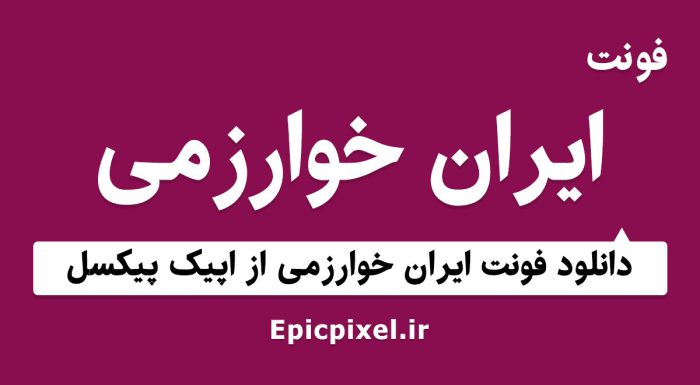
فونت ایران خوارزمی فارسی
فونت ایران خوارزمی یک فونت فارسی جدید و مدرن
اگر به دنبال یک فونت فارسی جدید و مدرن هستید که برای طراحی گرافیک، نشر محتوا و رسانههای اجتماعی مناسب باشد، ما به شما فونت ایران خوارزمی را پیشنهاد میکنیم. فونت ایران خوارزمی یک فونت بسیار زیبا و حرفهای است که با تلفظ و قلم فارسی همخوان است و به شکل و شخصیت زبان فارسی توجه دارد. در این مقاله، ما قصد داریم به شما معرفی کنیم که فونت ایران خوارزمی چیست، چگونه میتوانید آن را دانلود و نصب کنید و چه کاربردهایی برای آن وجود دارد. همچنین، نظرات کاربران درباره این فونت را با شما به اشتراک میگذاریم و به سؤالات متداول شما پاسخ میدهیم.
معرفی فونت ایران خوارزمی
فونت ایران خوارزمی یک فونت فارسی است که توسط شرکت ایران خوارزمی طراحی و تولید شده است. این شرکت یکی از پیشروان در زمینه تولید نرمافزارهای زبانشناسی، هوش مصنوعی و طراحی گرافیک است و با هدف ارتقای کیفیت و استاندارد زبان فارسی در فضای مجازی فعالیت میکند. فونت ایران خوارزمی یکی از جدیدترین و محبوبترین محصولات این شرکت است که در سال ۱۴۰۲ روانه بازار شده است.
تاریخچه و منشأ فونت ایران خوارزمی
فونت ایران خوارزمی بر اساس الگوریتمهای پیشرفته هوش مصنوعی و زبانشناسی طراحی شده است. این فونت با تحلیل دادههای بزرگ متنی فارسی، الگوهای زبانی، ساختار صوتی و نگارشی، تلفظ و قلم فارسی را شناسایی و بهینهسازی کرده است. هدف از طراحی این فونت، ارائه یک فونت فارسی با کدگذاری استاندارد، قابل خواندن، مناسب برای صفحات وب و رسانههای دیجیتال، هماهنگ با زبانهای دیگر و دارای زیبایی بصری است.
فونت ایران خوارزمی دارای ويژگيها و مزاياي بسياري است كه برخي از آنها عبارتند از:
قابليت پشتيباني از زبانهاي ديگر با الفباي لاتين (انگليسي، فرانسوي، آلماني، اسپانيولي و …)
قابليت نمايش در سطح بالا در صفحات وب با رزولوشنهاي مختلف
قابليت حفظ كيفيت در چاپ با رزولوشنهاي بالا
قابليت تغيير اندازه، رنگ، ضخامت و فرم بدون از دست دادن زيبايي و خوانايي
داراي حروف و اعراب منحصر به فرد و متناسب با شكل و شخصيت زبان فارسي
داراي انواع حروف ساده، پررنگ، كج، ضخيم و نازك
داراي انواع علائم نگارشي، رياضي، علمي و فني
داراي انواع ارقام فارسي، عربي، انگليسي و رومي
داراي انواع سمبلها و آيكونهاي گرافيكي
کاربردهای فونت ایران خوارزمی
فونت ایران خوارزمی یک فونت چند منظوره است که برای کاربردهای مختلف مناسب است. در این بخش، ما به برخی از کاربردهای فونت ایران خوارزمی در زمینههای مختلف میپردازیم.
استفاده از فونت ایران خوارزمی در طراحی گرافیک
فونت ایران خوارزمی یک فونت بسیار مناسب برای طراحی گرافیک است. این فونت با زیبایی بصری، تعادل شکل، تطابق با زبانهای دیگر و قابلیت تغییرات ظاهری، میتواند به طراحان گرافیک کمک کند تا آثار جذاب و حرفهای خلق کنند. برخی از نمونههای استفاده از فونت ایران خوارزمی در طراحی گرافیک عبارتند از:
لوگو تصویر
لوگو شرکت ایران خوارزمی
لوگو بانک ملی ایران
لوگو دانشگاه تهران
نمونههایی از طراحی پوستر با فونت ایران خوارزمی
پوستر تصویر
پوستر روز ملی زبان فارسی
پوستر جشنواره فیلم فجر
پوستر کنسرت محسن چاوشی
استفاده از فونت ایران خوارزمی در نشر محتوا
فونت ایران خوارزمی یک فونت بسیار مناسب برای نشر محتوا است. این فونت با قابل خواندن بودن، استاندارد بودن، هماهنگ بودن با سئو و رسانههای دیجیتال، میتواند به نویسندگان و محتوای محتوا کمک کند تا متنهای جذاب و مؤثر بنویسند. برخی از نمونههای استفاده از فونت ایران خوارزمی در نشر محتوا عبارتند از:
نمونههایی از متنهای تبلیغاتی با فونت ایران خوارزمی
تبلیغ کتاب «هوش مصنوعی برای همه»
تبلیغ دوره آموزشی «طراحی وب با فونت ایران خوارزمی»
تبلیغ بازی «شاهنامه: قهرمانان ایران»
نمونههایی از مقالات وبلاگ با فونت ایران خوارزمی
استفاده از فونت ایران خوارزمی در رسانههای اجتماعی
فونت ایران خوارزمی یک فونت بسیار مناسب برای رسانههای اجتماعی است. این فونت با جذابیت، شخصیت، همخوانی و تفاوت، میتواند به کاربران رسانههای اجتماعی کمک کند تا پستها و استوریهای جالب و متفاوت بسازند. برخی از نمونههای استفاده از فونت ایران خوارزمی در رسانههای اجتماعی عبارتند از:
نمونههایی از پستهای اینستاگرام با فونت ایران خوارزمی
پست درباره روز زبان مادری
پست درباره نقد فیلم «ماجرای نیمروز»
پست درباره معرفی کتاب «هوش مصنوعی برای همه»
نمونههایی از استوریهای تلگرام با فونت ایران خوارزمی
استوری درباره تخفیف دوره آموزشی «طراحی وب با فونت ایران خوارزمی»
استوری درباره نظرهای کاربران درباره فونت ایران خوارزمی